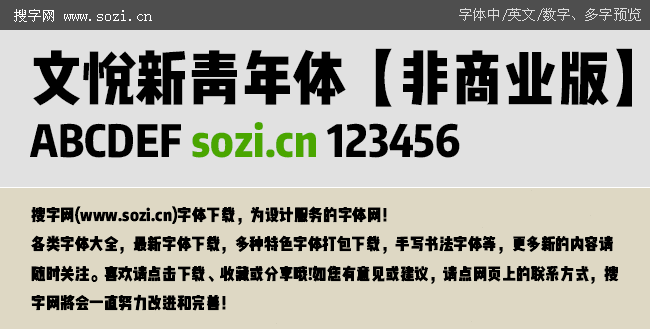
文悅新青年體【非商業(yè)版】
搜字網(wǎng)提供一款非常藝術(shù)的文悅新青年體【非商業(yè)版】下載,文悅新青年體是一款由黑體為原形進(jìn)行設(shè)計(jì)的中文藝術(shù)字體,該字體極具藝術(shù)感,簡(jiǎn)潔大方,適用于包裝印刷、廣告設(shè)計(jì)、平面設(shè)計(jì)、書籍報(bào)紙等領(lǐng)域。